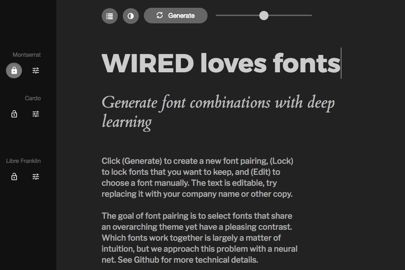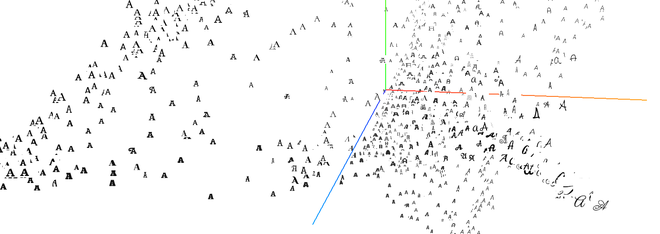
Sử dụng trí tuệ nhân tạo, một website có thể tự tạo ra các cặp font chữ theo yêu cầu của người dùng
Nó giúp cho các dự án cần sử dụng đến nhiều loại font chữ khác nhau không còn gặp khó khăn khi triển khai nữa.
Một ví dụ cho việc kết hợp nhiều kiểu font chữ khác nhau.
Bất kỳ chuyên gia sắp xếp bản in nào cũng có thể nói với bạn, việc ghép hai loại font chữ với nhau trong một dự án thiết kế phức tạp hơn bạn tưởng nhiều như thế nào. Phụ thuộc vào mục tiêu của bạn (ví dụ để tạo ra sự cân bằng hay hướng tới sự căng thẳng, hay để giới thiệu một đoạn nội dung cụ thể nào đó), có rất nhiều cách tiếp cận khác nhau.
Nhưng nếu bạn chỉ là một tay mơ và cần một đến sự giúp đỡ nào đó để một vài loại font chữ nào đó có thể làm việc trơn tru với nhau thì sao? Hãy dùng thử dự án mới của kỹ sư thiết kế Jack Qiao, Fontjoy.com. Trang web dễ sử dụng này sẽ tạo ra các cặp font chữ theo yêu cầu của bạn, và điều đáng ngạc nhiên là nó làm khá tốt nhiệm vụ của mình.
Bạn có thể sử dụng gần 2.000 font chữ (tất nhiên nhờ sự giúp đỡ của Google) và thiết lập nó thành sự lựa chọn chính của mình khi trang web lướt qua hàng loạt khả năng cho hai loại font chữ khác nhau. Và tất nhiên, bạn cũng có thể lựa chọn và đưa ra những lựa chọn về cặp font chữ của riêng mình.
Để xây dựng nên hệ thống thông minh này, Qiao trích xuất các vector tính năng từ hình ảnh của các font chữ, do đó anh có thể sử dụng các vector số học này để so sánh chúng với nhau. Ý tưởng này có thể được sử dụng để tìm ra các loại font nào phù hợp với nhau, và vì vậy có thể mở rộng để ghép các cặp font dựa trên những đặc điểm chung giữa chúng và những điểm khác biệt để phân biệt chúng với font chữ khác.
Cách sắp xếp các chữ A dựa trên những đặc điểm chung về vector.
Với một vài phép toán thông minh, Fontjoy đã sản sinh ra các cặp font chữ trông rất thuận mắt. Tuy nhiên, nếu bạn là một nhà thiết kế dày dặn kinh nghiệm, bạn cũng có thể xem đây như một khởi đầu cho dự án in ấn riêng của bạn, hay chỉ đơn giản thử nghiệm và tìm cảm hứng mới cho điều gì đó phù hợp hoàn hảo với công việc của bạn.